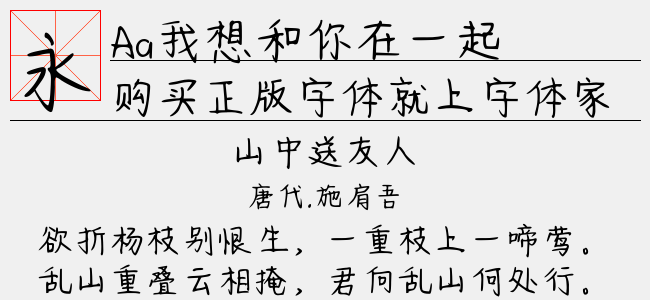
Aa我想和你在一起-Aa字体
Aa我想和你在一起是一款大小5.39 M的Aa字体字体,主要特征是手写,行书,手书风格,钢笔,,Aa我想和你在一起为TTF格式的文件,采用安装嵌入,包含了英文、拉丁文以及日文等符号,字宽中等(正常),当前版本是Version 1.000,共计6763个汉字以及附加其他英文字体和阿拉伯数字。
字体作者:Aa字体
字体名称:Aa我想和你在一起